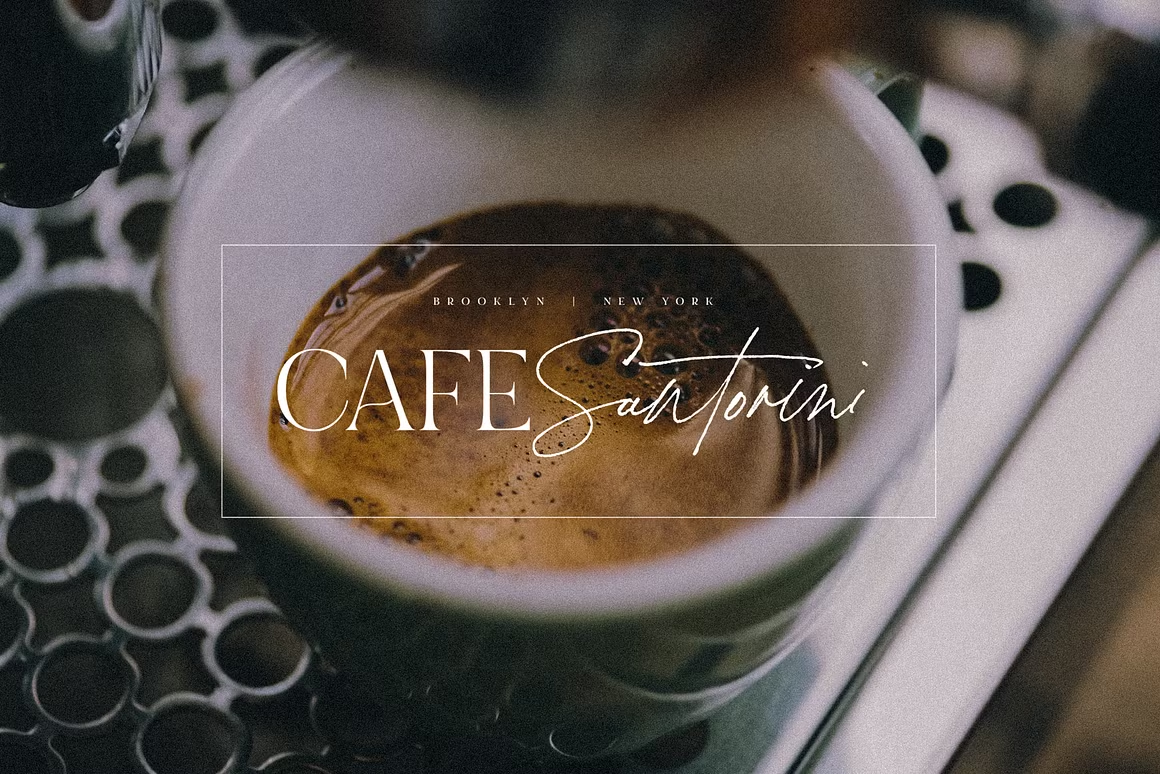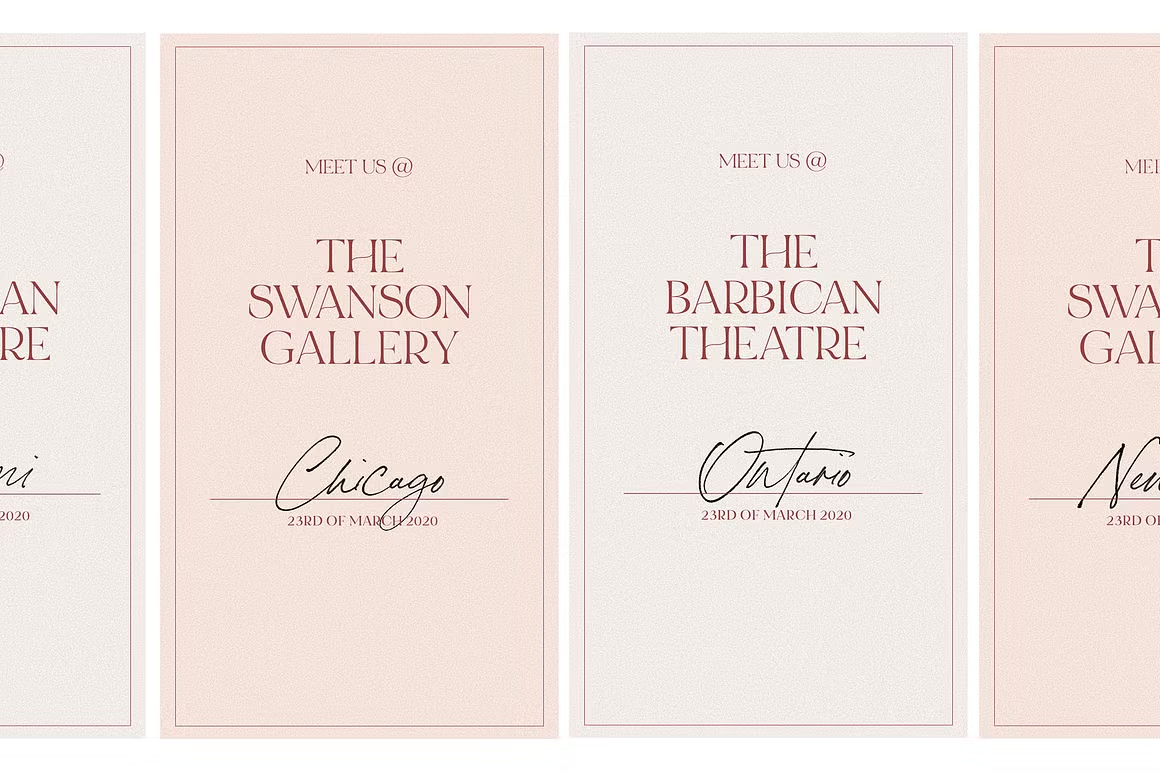
Bon Vivant Font
Description de Bon Vivant Font
Si vous avez du style et aimez tout le luxe de la vie, vous êtes Bon Vivant ! Ajoutez également une touche de luxe et de style à vos projets avec la nouvelle collection de polices Bon Vivant. Le pack comprend des cadeaux de créateurs gratuits pour vous aider à laisser libre cours à votre créativité ! Parcourez les aperçus ci-dessus pour trouver l’inspiration créative et voir ce que vous pouvez réaliser.
Police de script Bon Vivant
Police Bon Vivant Serif
Détails:
Le script est disponible sous forme de police Bitmap OpenType SVG et de police Regular Opentype. – Le script comprend une large sélection de ligatures automatiques – elles donnent à votre texte l’apparence d’une écriture manuscrite naturelle plutôt que d’une police. Le script comporte des lettres majuscules et minuscules, des signes de ponctuation et des chiffres. Testez la police en tapant votre phrase/texte dans la zone d’aperçu du texte sur cette page.
L’empattement est disponible en 2 graisses, régulière et grasse. L’empattement comporte des lettres majuscules et minuscules ainsi que tous les signes de ponctuation et tous les chiffres. Testez la police en tapant votre phrase/texte dans la zone d’aperçu du texte sur cette page.
La police SVG est une police Raster Bitmap avec une taille et une résolution maximales. La police SVG peut être facilement saisie à une taille où les lettres majuscules mesurent un peu plus de 2 pouces de hauteur – sans perte de qualité ou de résolution. Pour les projets nécessitant une police de plus grande taille, vous devez utiliser la version vectorielle de la police, qui est également incluse dans le pack.
Prise en charge linguistique : actuellement, seul l’anglais est pris en charge, mais les accents suivants sont inclus : ¨ ˜ ´ ˆ ` ˚ ¸